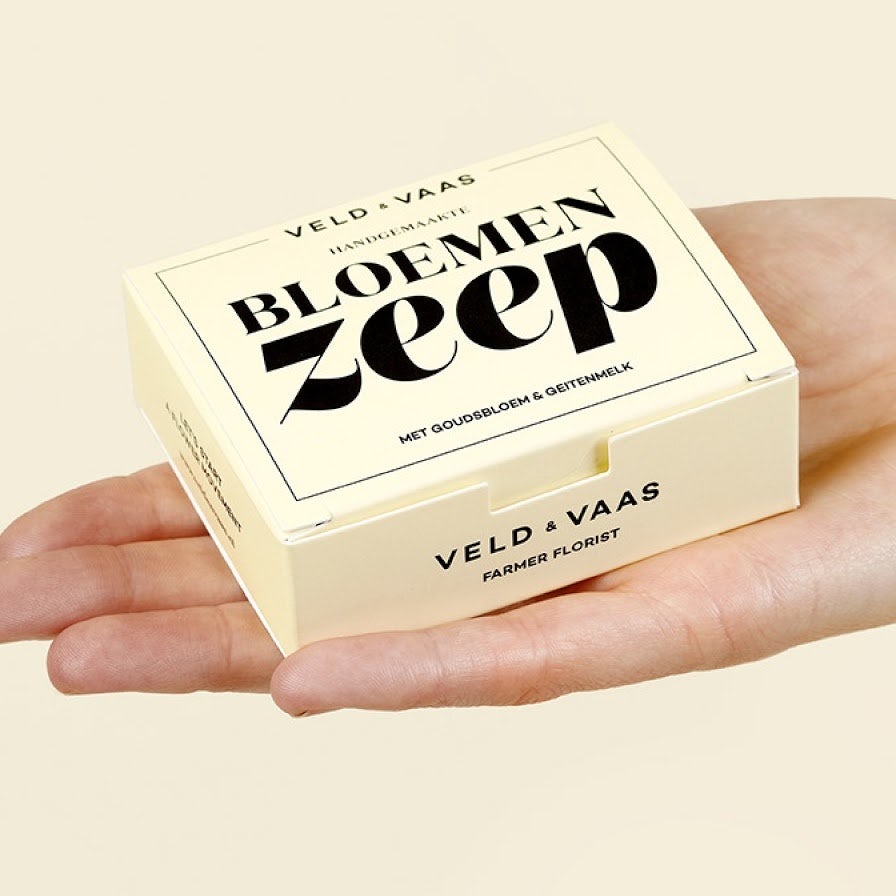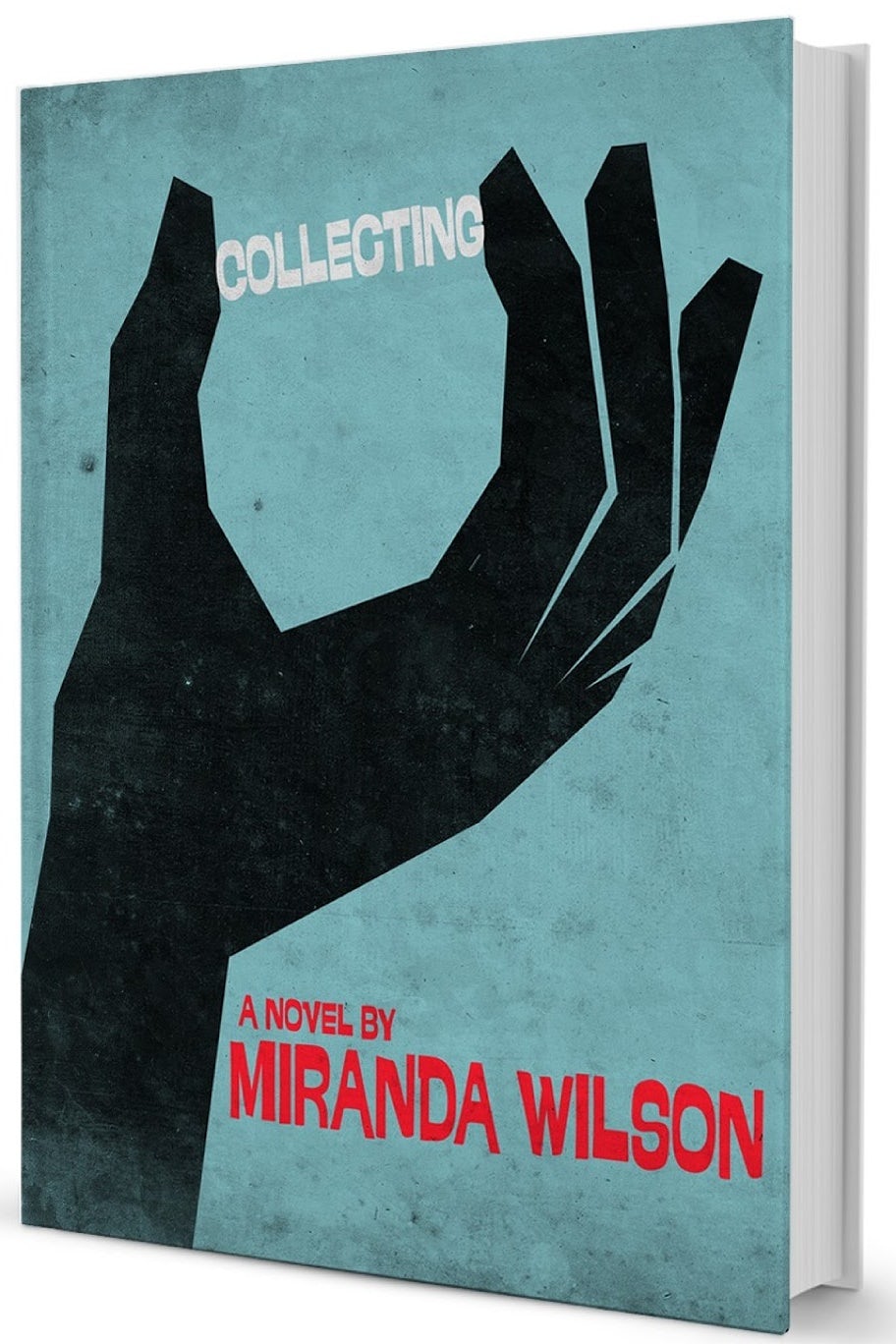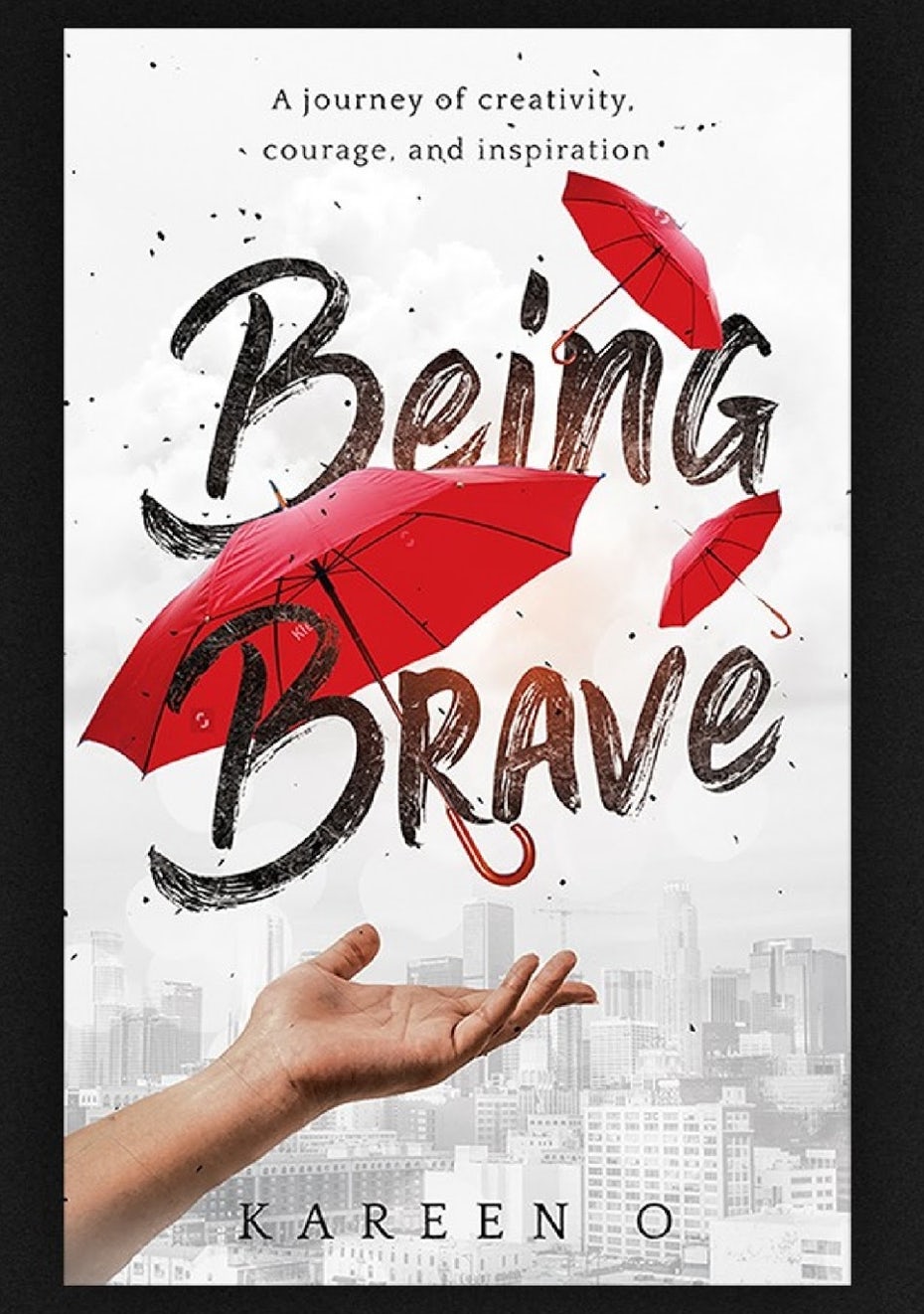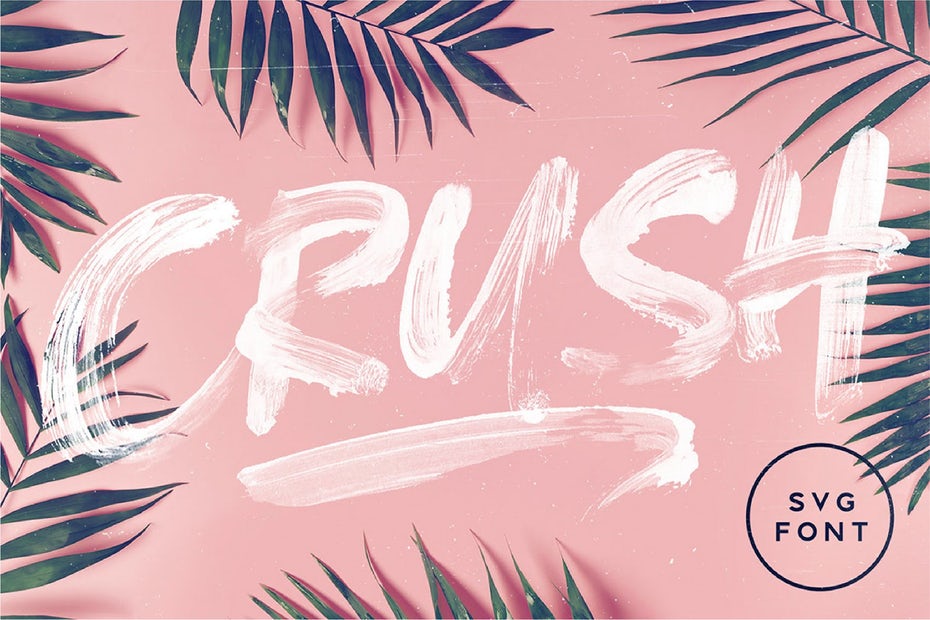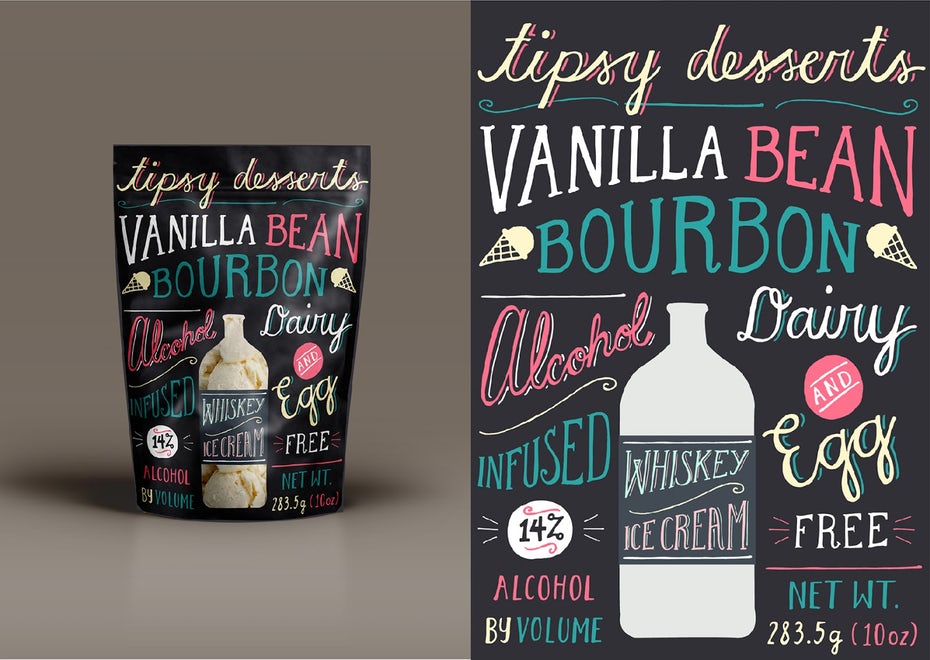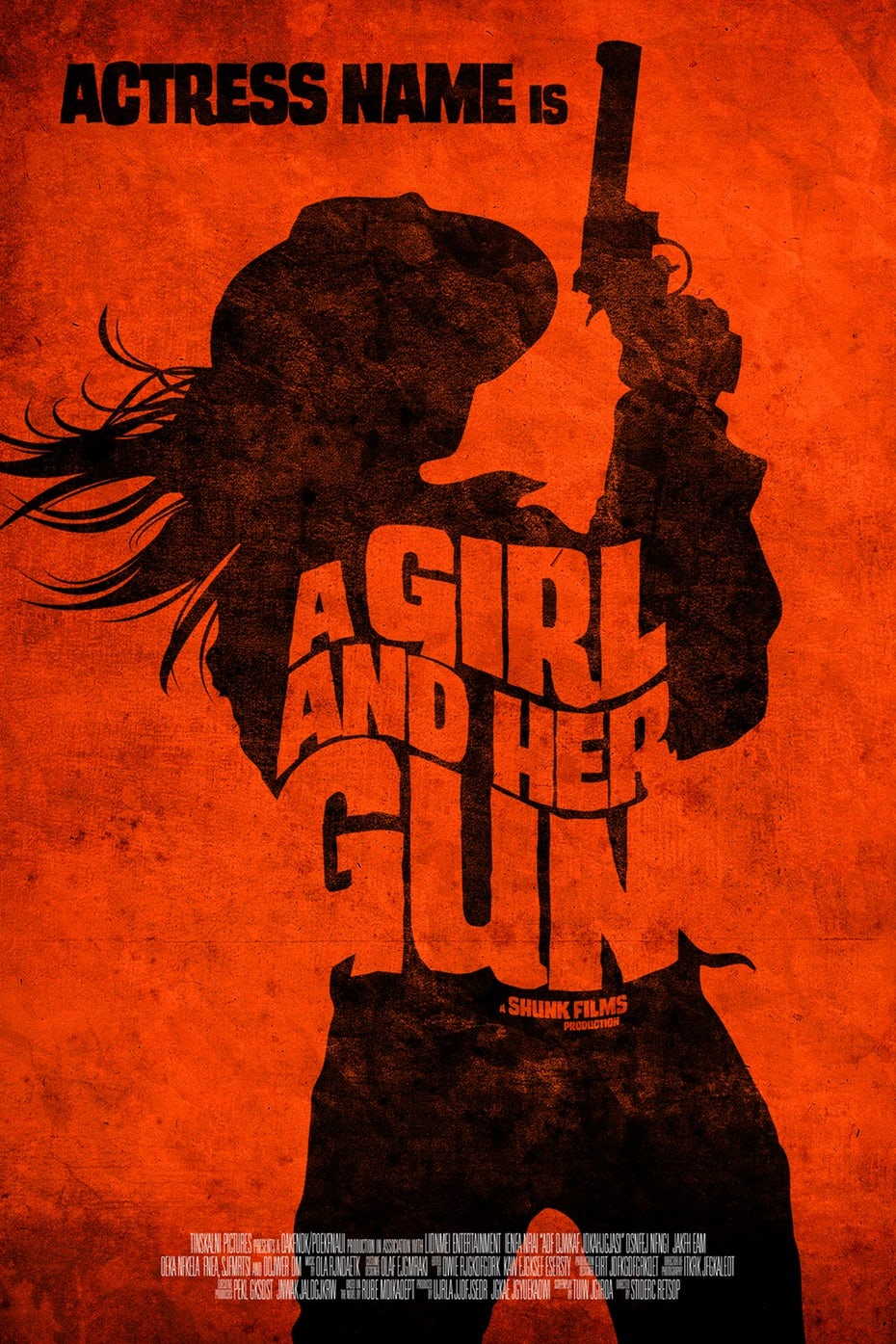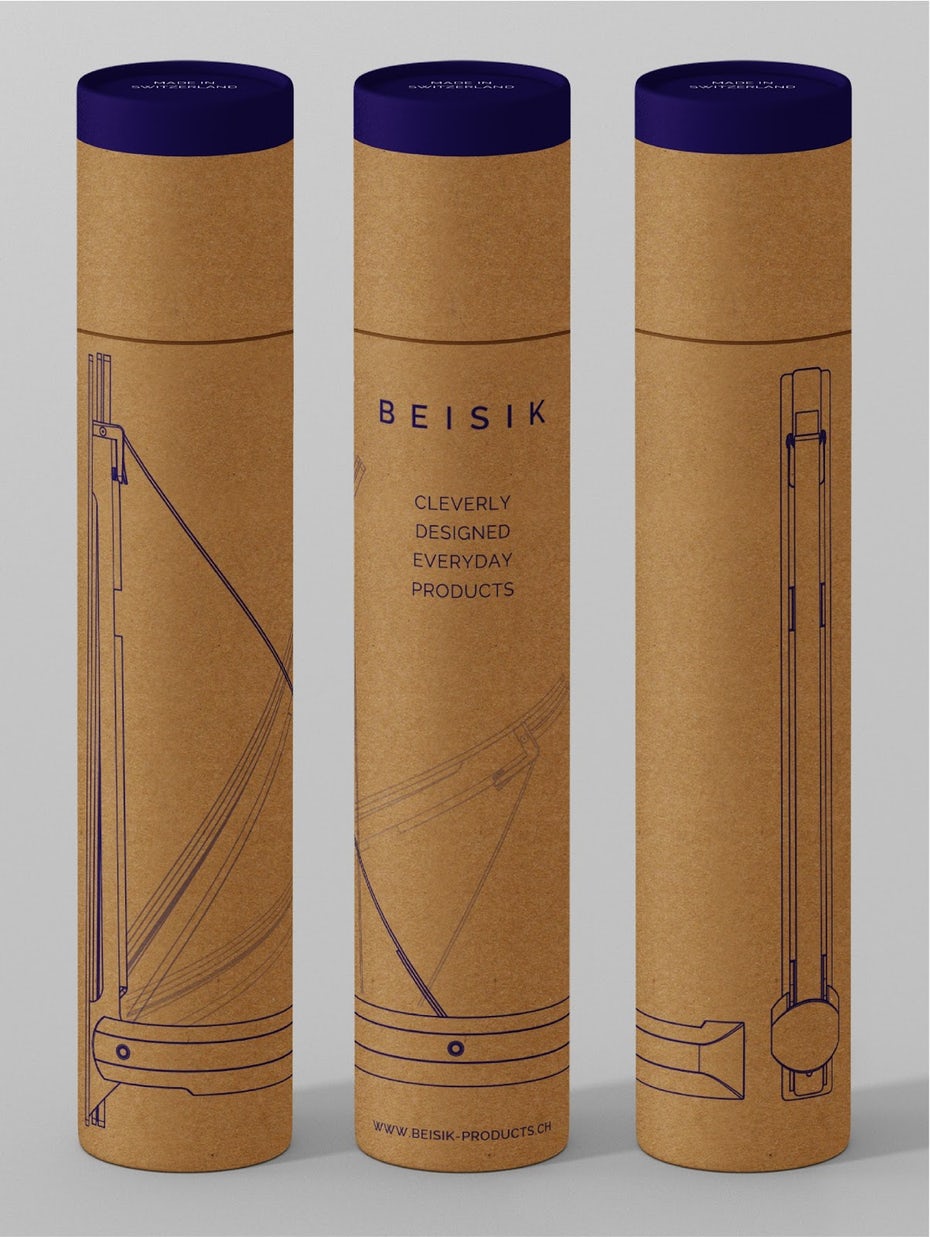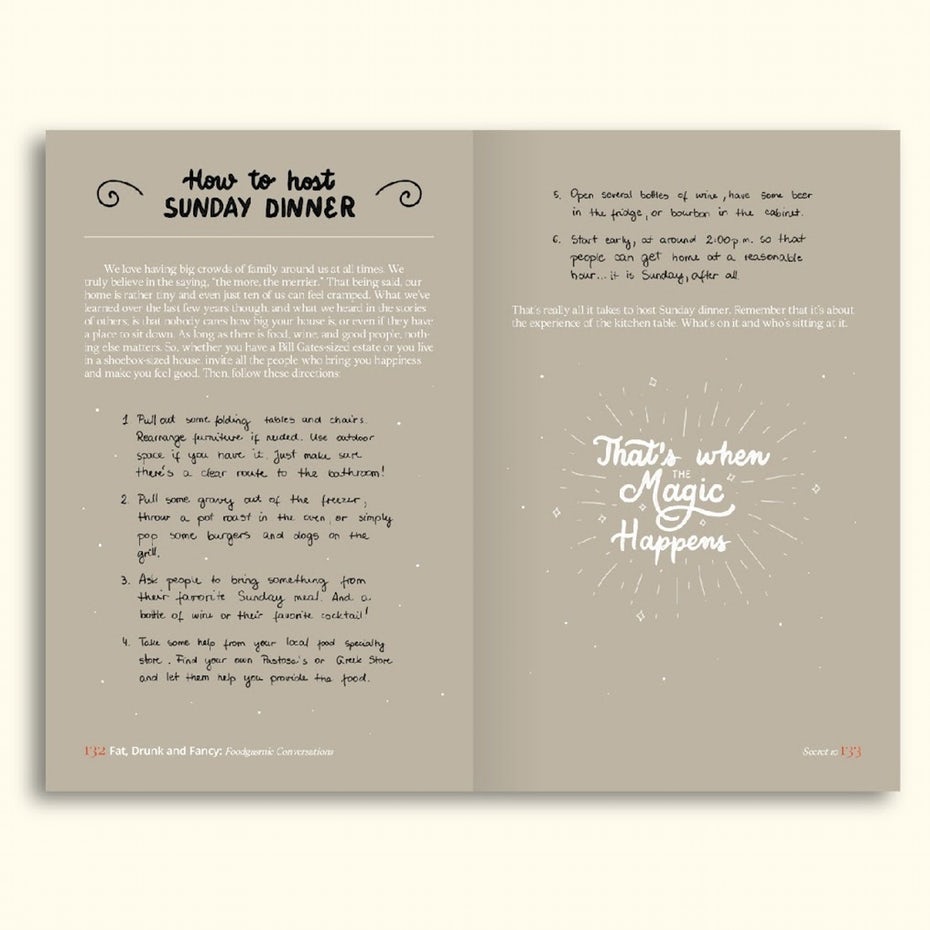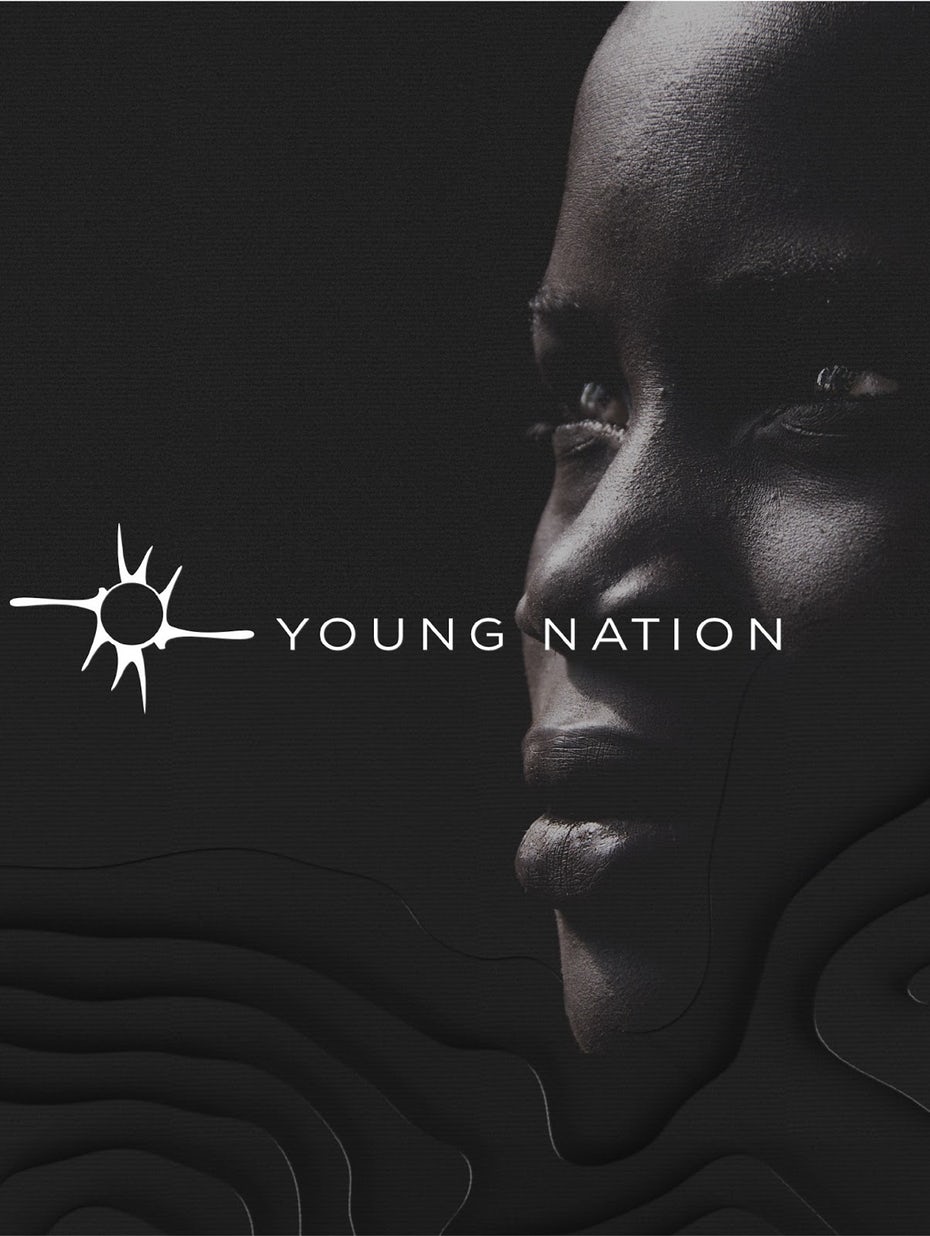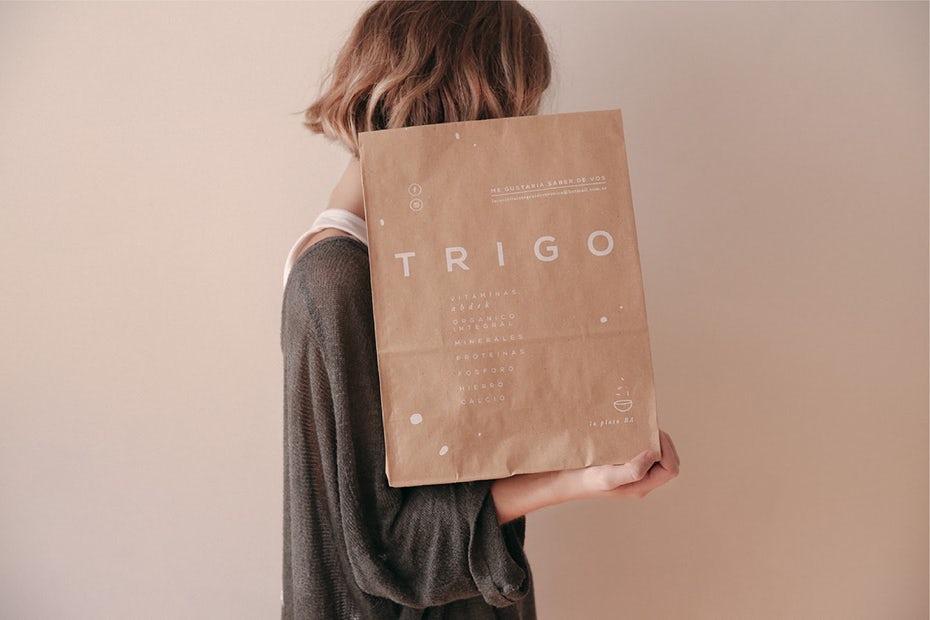
Mang những typography tuyệt đẹp vào trong thiết kế của bạn là một trong những cách hiệu quá nhất để giao tiếp với tư cách là một thương hiệu. Đó là lý do tại sao bắt kịp những xu hướng font chữ mới nhất là hoàn toàn cần thiết.
Phông chữ sáng tạo không chỉ mang thông điệp của bạn mà còn tạo ra tác động trực quan và kích thích cảm xúc. Typhography có thể thể hiện niềm vui hoặc sự sợ hãi, sự ồn ào hoặc yên tĩnh. Hoặc nó có thể khiến bạn cười to, co rúm, thở hổn hển – và chứa đựng mọi thứ trong đó.
Hãy cùng RGB nhìn vào những xu hướng phông chữ mới nhất năm 2019 dưới đây, để bạn có thể sử dụng linh hoạt trong thiết kế của mình nhé!
9 xu hướng font chữ dự báo sẽ thu hút trong năm 2019
1. Phông chữ đậm và cực lớn
2. Phông chữ không chân “sans serif” đơn giản
3. Phông chữ dạng cổ điển
4. Phông chữ dạng phác thảo
5. Phông chữ dạng viền
6. Phông chữ serif (Có chân) tương phản cao
7. Phông chữ phá cách
8. Phong chữ lộn xộn
9. Chữ viết tay độc đáo
1. Font chữ đậm, cực lớn
Trong năm 2019, các phông chữ cực lớn, ấn tượng và in đậm sẽ tiếp sẽ ngày càng phổ biến hơn với những nhà thiết kế đang tìm cách để gây ấn tượng. Những typography ấn tượng này thống trị thiết kế như một yếu tố thiết kế chủ đạo và là một sự lựa chọn hiển nhiên nếu bạn muốn thông điệp của bạn rõ ràng.
Phông chữ đậm làm cho logo của bạn bật lên trên bất cứ thứ gì bạn đặt nó vào. Áp phích và tờ rơi sẽ dễ nhìn thấy từ đằng xa. Và trang web của bạn sẽ toát lên một cá tính mạnh mẽ.
2. Phông chữ không chân “sans serif” đơn giản
Gặp gỡ người anh em đối nghịch với typography đậm: font chữ sans serif đơn giản (là font chữ không có serif, cái móc chân nhỏ ở mỗi góc chữ), sẽ tiếp tục là một sự yêu thích cho các thiết kế đơn giản trong 2019. Nhờ vào sự đơn giản, những font chữ này rất dễ làm việc. Nó không yêu cầu trực quan và rất hiệu quả khi sử dụng tốt.
Sans serif đơn giản làm cho các tác phẩm trong thoáng và mềm mại với cảm giác bình yên và yên tĩnh. Cho nó không gian hoặc bạn mạo hiểm lấy đi sự quyến rũ của nó.
3. Phông chữ cổ điển
Chúng ta càng tiến về tương lai, chúng ta càng hoài niệm về quá khứ. Điều đó đúng với thiết kế thời trang, nội thất, và cả đồ họa. Vì vậy, không ngạc nhiên khi năm 2019 sẽ thấy nhiều font chữ đang tái hiện và cố gắn nắm bắt quá khứ.
Sử dụng một font chữ hoài cổ có thể làm một gói thiết kế hoặc logo trở nên thanh lịch và nghiêm túc. Hoặc táo bạo, nhưng hoài cổ và tinh tế. Nếu bạn muốn đem một cảm giác cổ điển đến với thế giới hiện đại, phong cách này là dành cho bạn.
4. Phông chữ dạng phác thảo
Kiểu phông chữ phác thảo sẽ không bao giờ bị lỗi thời. Chúng mang đến sự uyển chuyển, linh hoạt của chữ viết tay và được xây dựng trên kiểu chữ tinh tế của các nhà thư pháp. Tuy nhiên, phông chữ này đã phát triển rất nhiều và năm 2019 chúng sẽ mang theo nhiều hình dạng và phong cách khác nhau. Chúng có thể cổ điển hoặc phá cách, nghiêm túc hoặc tươi vui. Bất kể bạn chọn phong cách nào, hiệu quả sẽ vô cùng bất ngờ khi sử dụng loại kiểu chữ này.
5. Phông chữ dạng viền
Cho dù bạn đang tìm cách làm nổi tiêu đề, chủ đề hay vài bản thảo hoặc làm cho bố cục trở nên nhẹ nhàng, phông chữ này sẽ giúp bạn. Với phong cách hiện đại từ kiểu chữ dạng viền này vô hình chung đã giúp các thương hiệu trông tiên tiến và chuyên nghiệp. Tìm hiểu về nó với hình thái và kích cỡ khác nhau: to hay nhỏ, thường hay đậm, cô đọng hay in nghiêng, mộc mạc và thủ công hay mượt mà và sắc sảo.
6.Font chữ serif (Có chân) tương phản cao
Font chữ serif tương phản cao mang thông điệp rất mạnh, nhưng tinh tế và trong năm 2019 chúng sẽ bao phủ khắp nơi. Bạn sẽ nhận ra độ tương phản cao trong cỡ chữ: nét lên thường mỏng hơn nét xuống, và những phông chữ này phóng đại sự tương phản, tạo nên hiệu ứng mạnh mẽ.
Sự tương phản này làm chúng trở nên rất táo bạo, kiểu như nguyên thủy, với một yếu tố tinh tế. Khi bạn sử dụng phong cách typography này, bạn sẽ dễ dàng phân loại, sắp xếp thiết kế của mình.
7. Font chữ phá cách
Tìm một typography tươi vui trong năm 2019 mà cứng rắn, vụng về, nhưng vẫn quyến rũ. Mọi người đang bị thu hút mởi hình ảnh phá cách mà không cân bằng, không ngờ tới và thậm chứ hài hước vì nó mang cho họ một sự phá cách từ sự bóng bẩy xung quanh.
Font chữ phá cách khá dễ tiếp cận và hoàn hảo cho những sản phẩm dùng để mang lại nụ cười cho khán giả của bạn. Hãy xem qua những ví dụ biến thông điệp in ấn và kỹ thuật số trở thành một trải nghiệm mới mẻ và tươi vui.
8. Font chữ “lộn xộn”
Font chữ đậm, serif, và dạng viền đều có bản đối nghịch lộn xộn và có thể sử dụng như nền cho xu hướng font chữ thô và lộn xộn. Chúng thoát khỏi cái “đẹp” như chúng ta biết, và tạo nên một hình thái sắc đẹp mới – sắc đẹp mà không quan tâm về điều gì.
Đón chờ xem thêm nhiều font chữ không chính thống này với thái độ punk mà ngầu không cần cố gắng. Nếu bạn cảm thấy cần phải thoát khỏi sự thông thường – và nếu bạn có thể xử lý sự lộn xộn – những kiểu chữ này là dành cho bạn.
Chữ viết tay có thể làm mọi thứ. Bất cứ hình dạng và kích cỡ nào. Bất cứ phong cách nào. Nhưng quan trọng nhất là bạn sẽ luôn có một thứ gì đó độc nhất, điều đó sẽ gia tăng phần cá tính cho thương hiệu hoặc sản phẩm của bạn.
2019: Năm của “mọi thứ đều có thể”
Như mọi năm, nhà thiết kế ở mọi nơi trên thế giới đang tìm cách vượt qua những rào cản, tạo mới và tái tạo! Đón chờ xem một chút của tất cả mọi thứ – từ nhẹ nhàng đến táo bạo, viết tay đến kỹ thuật số. tinh tế đến lộn xộn (và tất cả mọi thứ). Và chúng tồn tại trong một kiểu chữ hài hòa hoàn hảo.